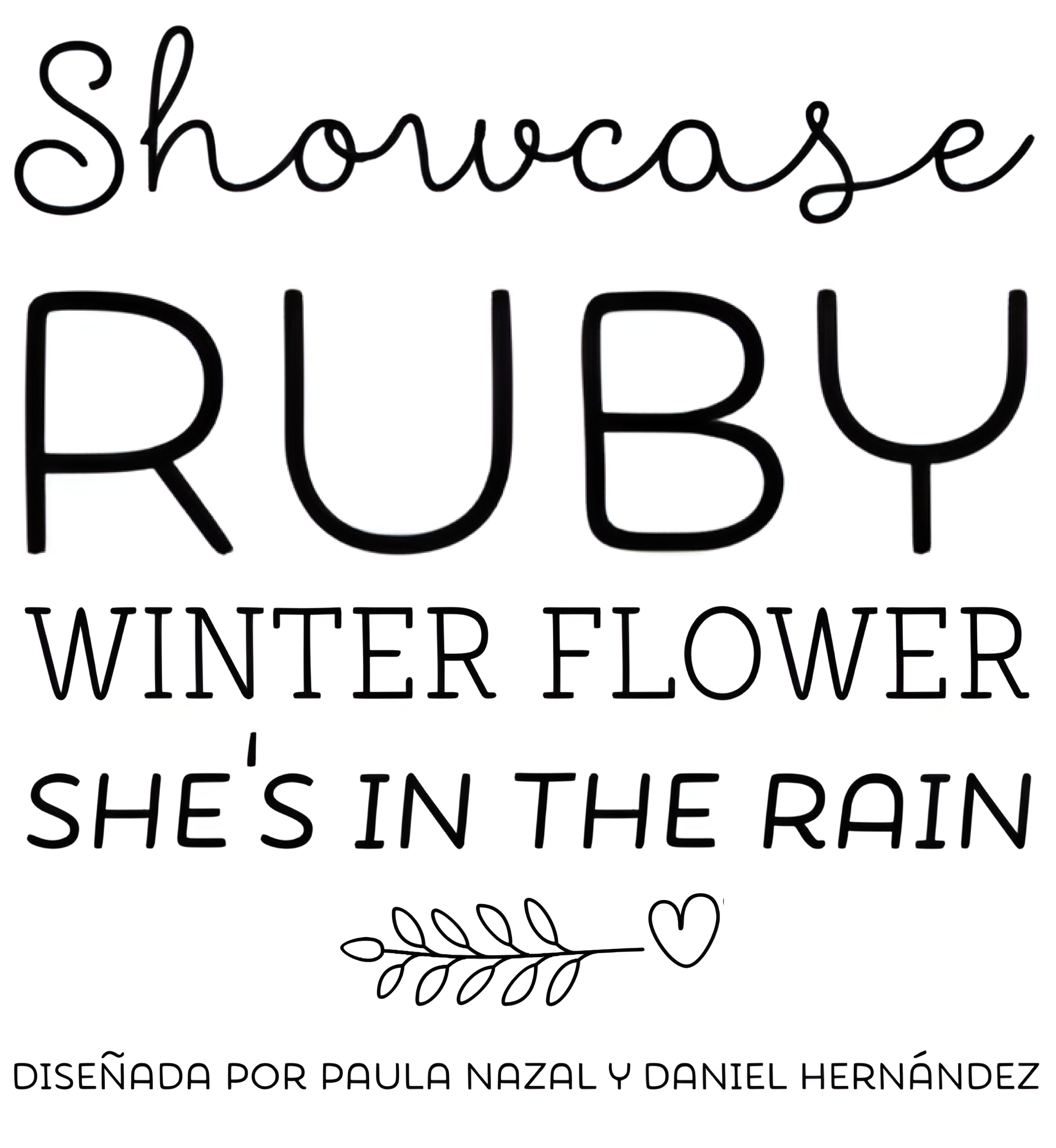
| Año | 2014 |
| Créditos | Paula Nazal Selaive, Daniel Hernández |
| Descripción | Showcase, el nuevo tipo de letra de Daniel Hernández y Paula Nazal es una fuente hecha a mano que consiste en un conjunto de tipos que se componen de cuatro estilos, uno script, uno sans, un slab, sans mini y finalmente un conjunto de ornamentos y dingbats, todos hechos para trabajar juntos en el mismo lenguaje. Está inspirado en un bolígrafo que escribe diferentes tipos de letra y ornamentos, y que casualmente forma una familia armoniosa. Showcase es muy fácil de usar y permite una gran versatilidad, puede utilizarse tanto en una revista como en un restaurante, a través de escaparates, cafeterías, ¡y realmente de cualquier forma que se te ocurra! |
| Clasificación | Títulos, Dingbats |
| Familia(s) | Script, Sans Mini, Sans Mini Italic, Slab, Slab Italic, Sans, Sans Italic, Ornaments |